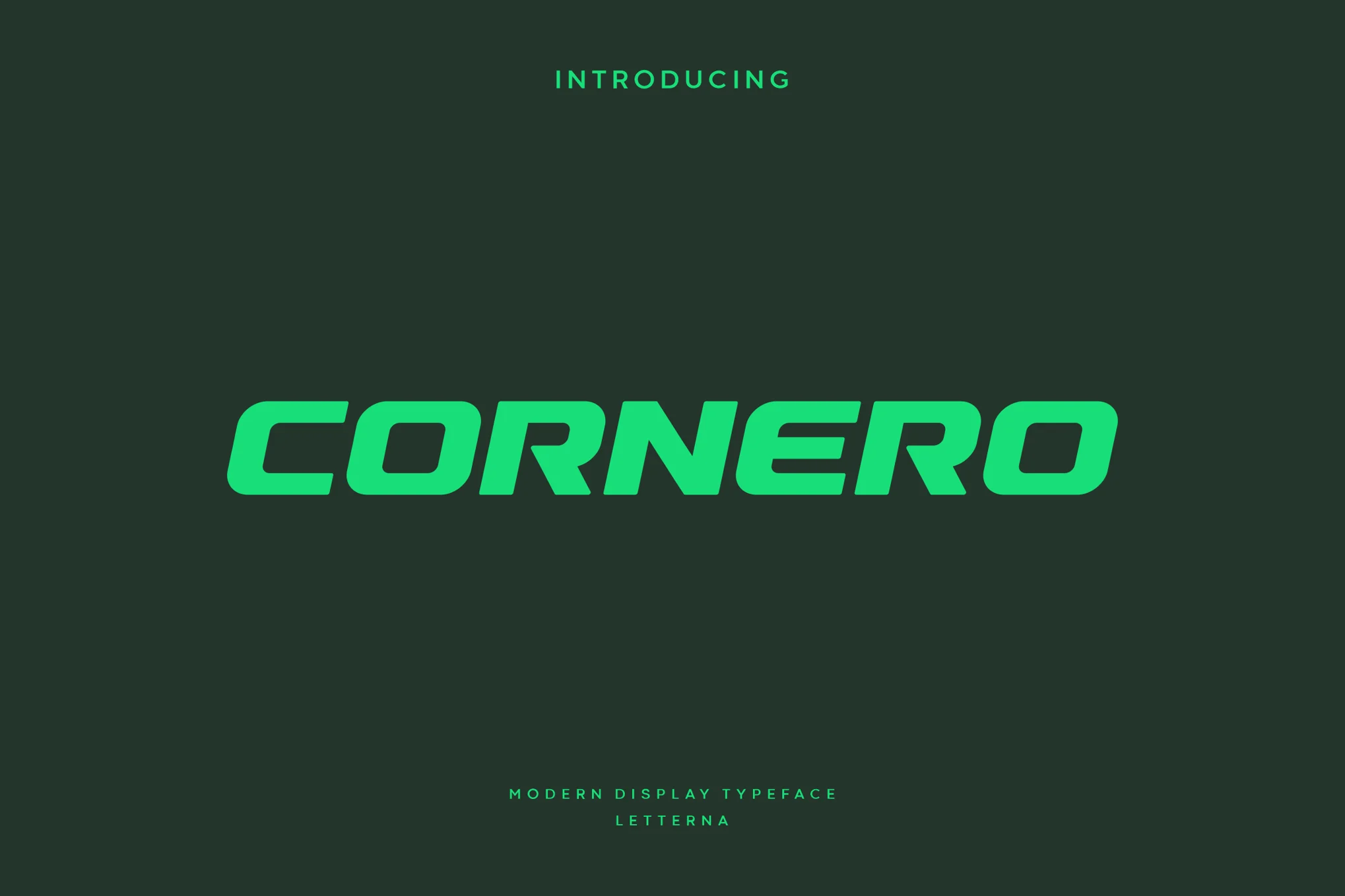
دانلود فونت Cornero – Modern Sport Typeface
Cornero یک فونت نمایشگر مدرن است که به طور خاص برای برندسازی ورزشی، تیتر و نیازهای برجستهتر تایپوگرافی ساخته شده است. این فونت با یک سبک جدید و جدید تمام کلاه ارائه می شود، طراحی شما را به یاد ماندنی تر می کند، برای اضافه کردن این فونت به تم های ورزشی، فنی، اکشن و آینده عالی است. Cornero برای سبک اکشن جسورانه و احساس مدرن ایجاد شده است، بنابراین از ایجاد هر پروژه ای که ایده های اصلی شما را به نمایش می گذارد لذت ببرید.